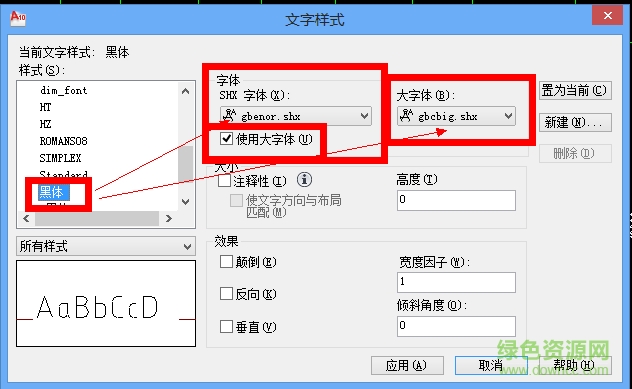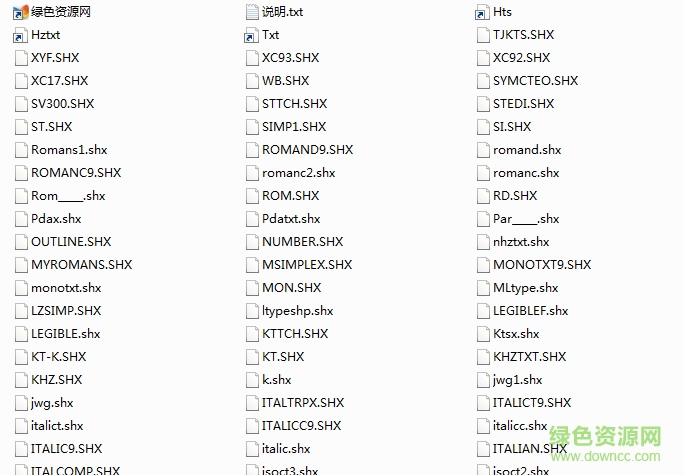
cad2008字體大全
CAD中常用字體有哪些?
在CAD中最常用的字體當(dāng)屬*.shx字體了。
SHX字體有g(shù)benor.shx、geniso.shx,大字體有hztxt.shx、gbcbig.shx等,一般各個(gè)公司和個(gè)人都有各自規(guī)定或喜愛(ài)的字體,因此也沒(méi)有特別的統(tǒng)一。
cad2008常用字體
常用的SHX字體:
Txt是最常用的小字體文件,包含數(shù)字、字母和一些簡(jiǎn)單的符號(hào),圖形比較簡(jiǎn)單
monotxt等寬的txt字體:在這種字體中,除了分配給每個(gè)字符的空間大小相同(等寬)以外,其他所有的特征都與txt字體相同。因此,這種字體尤其適合于書(shū)寫(xiě)明細(xì)表或在表格中需要垂直書(shū)寫(xiě)文字的場(chǎng)合。
romans這種字體是由許多短線段繪制的roman字體的簡(jiǎn)體(單筆劃繪制,沒(méi)有襯線)。該字體可以產(chǎn)生比txt字體看上去更為單薄的字符。
romand這種字體與romans字體相似,但它是使用雙筆劃定義的。該字體能產(chǎn)生更粗、顏色更深的字符,特別適用于在高分辨率的打印機(jī)(如激光打印機(jī))上使用。
romanc這種字體是roman字體的繁體(雙筆劃,有襯線)。romant這種字體是與romanc字體類(lèi)似的三筆劃的roman字體(三筆劃,有襯線)。
italicc這種字體是italic字體的繁體(雙筆劃,有襯線)。
italict這種字體是三筆劃的italic字體(三筆劃,有襯線)。scripts這種字體是script字體的簡(jiǎn)體(單筆劃)。這種字體是script字體的繁體(雙筆劃)。
greeks這種字體是Greek字體的簡(jiǎn)體(單筆劃,無(wú)襯線)。greekc這種字體是Greek字體的繁體(雙筆劃,有襯線)。gothice哥特式英文字體。gothicg哥特式德文字體。
gothici哥特式意大利文字體。
syastro天體學(xué)符號(hào)字體。
symap地圖學(xué)符號(hào)字體。symath數(shù)學(xué)符號(hào)字體。symeteo氣象學(xué)符號(hào)字體。
Symusic音樂(lè)符號(hào)字體。
cadshx字體
大字體文件:
hztxt單筆劃小仿宋體。
hzfs單筆劃大仿宋體。
china雙筆劃宋體。
在工程制圖中,最常用的字體是txt,hztxt即txt.shx和hztxt.shx,這里就需要一個(gè)txt就解決了一切英文字,包括數(shù)字;hztxt解決了所有中文字。當(dāng)然漢字都可以用宋體替代,但也可以用hztxt替代,意思是一樣的。宋體不是萬(wàn)能的,因?yàn)閣indows自己的宋體好像就有幾個(gè)不同版本。